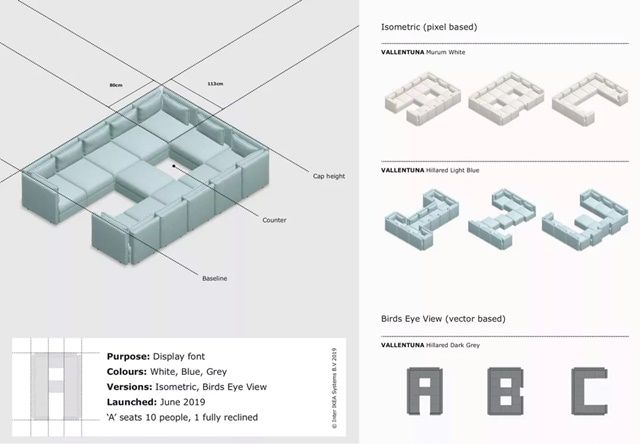
이케아, 소파로 만든 무료 폰트 출시
기업의 브랜드 폰트가 한층 더 진화했다.
가구 브랜드 이케아는 최근 ‘소파 산스(Soffa Sans)’라는 폰트를 무료로 공개했다. 특이한 점은 이 폰트가 소파를 이어 붙인 모양이라는 점이다. 기업들이 자사의 정체성이나 브랜딩을 강화하기 위해 브랜드 폰트를 내놓은 경우는 지금까지도 많았다. 하지만 이케아처럼 폰트에 자사의 제품을 그대로 가져다 폰트로 만들어 무료로 배포한 사례는 처음이다.
이케아에 의하면 소파 산스는 고객의 취향대로 선택해 만드는 온라인 플래너 서비스 ‘디자인 유어 오운 소파(Design your own sofa)’에서 영감을 받아 개발됐다. 고객이 취향대로 직접 소파를 만들 수 있는 서비스를 폰트에 적용한 것이다. 폰트를 공개하고 이케아는 ‘세상에서 가장 편안한 폰트’라는 설명을 붙였다.
소파 산스에는 이케아라는 가구 브랜드가 가진 비전과 브랜드 경험이 고스란히 녹아있다. 단순히 기업이 폰트를 만들어 배포하는 단계를 넘어서 폰트를 사용하는 유저가 기업이 전달하고자 하는 메시지를 직접 느낄 수 있도록 한다. 실제 이 프로젝트는 기업이 아니라 고객들로부터 출발했는데, 온라인 플래너 서비스에서 사람들이 소파로 다양한 알파벳과 숫자를 만들어내는 것에서 아이디어를 얻어 시작한 것이다. 고객의 행동을 면밀히 관찰해 자사의 커뮤니케이션 수단과 이벤트로 발전시킬 줄 아는 이케아의 기지와 기업의 브랜드 폰트가 얼마나 더 멋지게 진화할 수 있는지 보여준 멋진 사례다.
소파 산스의 실제 알파벳 26개를 모두 이케아 소파로 제작하게 되면 약 1억 6천만원의 비용이 든다. 이케아 웹사이트에서 폰트를 다운 받으면 해당 알파벳을 실제 소파로 만들었을 때 앉을 수 있는 사람의 수, 입체로 된 폰트(OTF), 평면으로 된 폰트(OTF)를 각각 볼 수 있다. 다만 아쉽게도 한글은 지원하지 않는다.